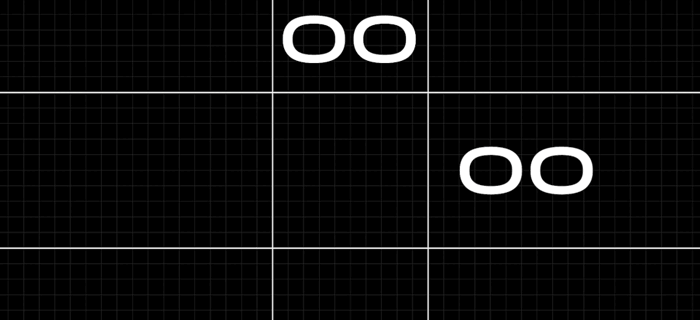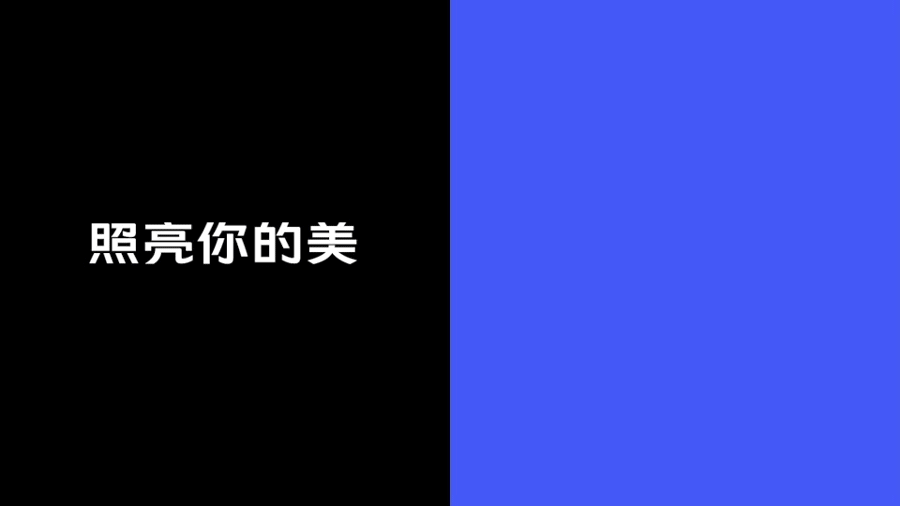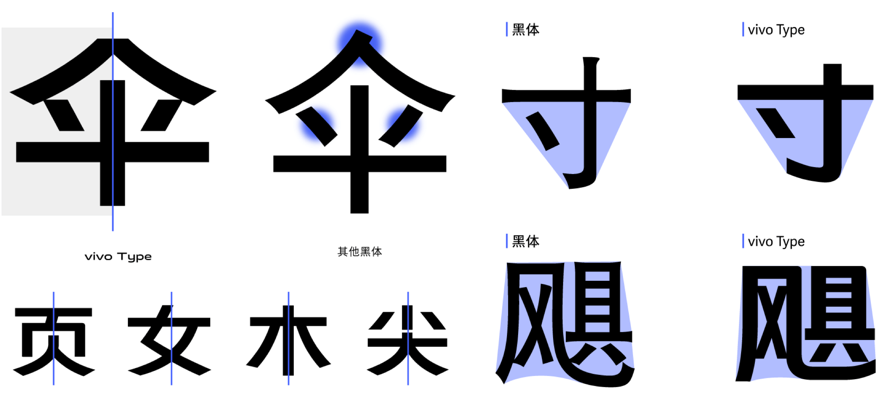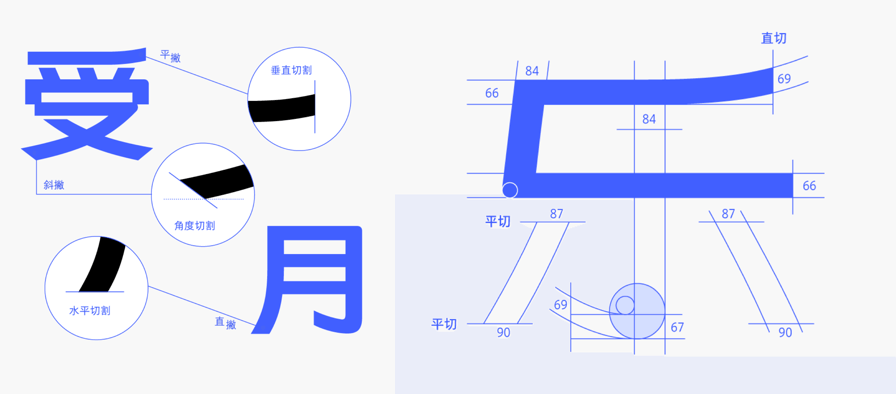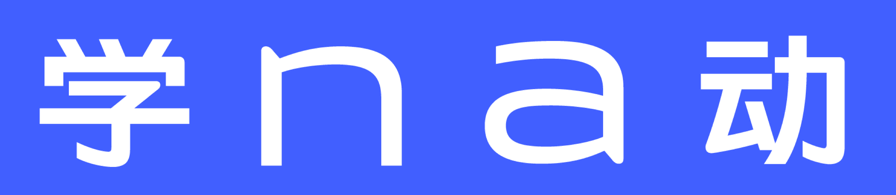
vivo
品牌定制字体
vivo Type
2019
品牌定制字体
vivo Type
2019
vivo Type是知名手机品牌vivo的专用字体,中文部分由方正字库设计师仇寅和汪文共同设计。vivo Type通过简洁、精致、理性的笔形处理,充分体现出了一个手机品牌所需要的现代科技感; vivo Type通过将字的重心显著提升,使得字势挺拔生动,具有高雅气质,并呈现出年轻朝气的精气神;此外, vivo Type字型扁平、笔画形态温和,不仅拥有独特的时尚气质,还能够在众多字体中脱颖而出
vivo Type与其他黑体相比
vivo Type的笔画设计,以平切和直切为主体手段,体现出了现代科技感
vivo Type的中心显著提升,呈现出年轻朝气的精气神
vivo Type的扁平设计,跳脱出了常见的黑体的形态,拥有了独特的时尚气质
vivo Type专门制作了适合香港地区使用的Big5版本字形,让vivo在使用繁体中文的地区也可以畅通无阻
vivo Type实际应用场景